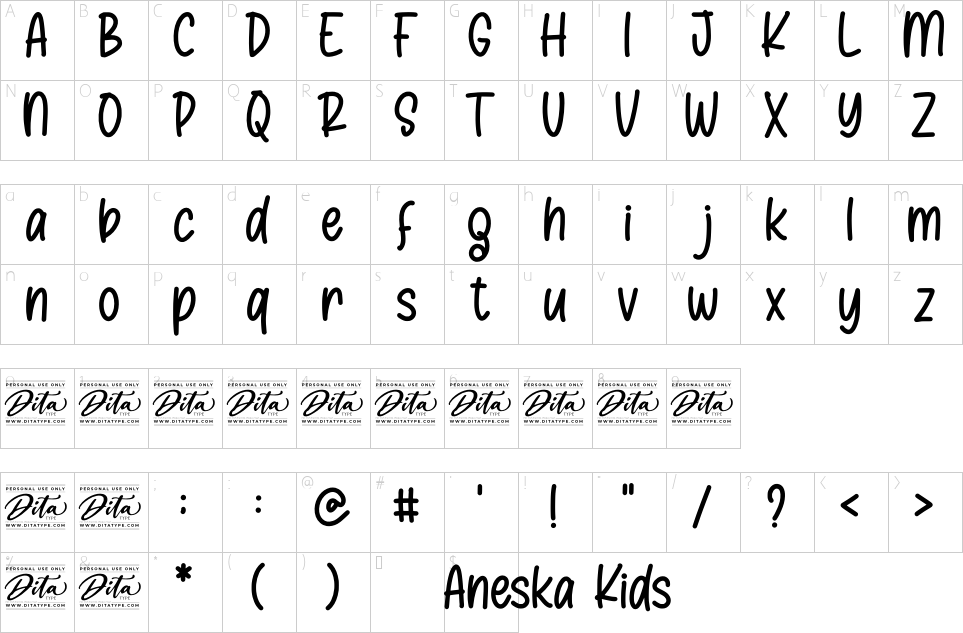
Descubra a encantadora Aneska kids Font, perfeita para os mais novos. Desenvolvida pela Dita type, esta fonte kids é uma escolha ideal para crianças, caracterizada por ser delicada e divertida. A Aneska kids é perfeita para trabalhos escolares, desenhos infantis e até mesmo para criar cartões personalizados. É uma fonte que combina facilmente com outras, proporcionando harmonia em suas criações. Com mais de 9.361 downloads, é uma opção segura e popular, tornando-a uma excelente escolha para aqueles que buscam um recurso gráfico de qualidade para seu projeto. Descubra agora e deixe os seus trabalhos ganharem vida através dessa bela fonte kids.